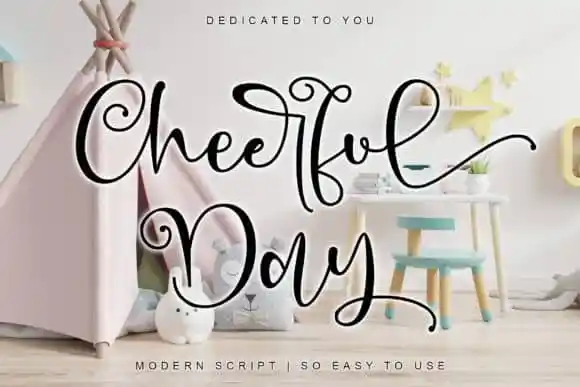
Cheerful Day Calligraphy Font – Download Grátis
Introduzimos a Cheerful Day Calligraphy Font – uma fonte delicada e romântica, escrita à mão com seu fluxo poético. Inspirada no desenho natural da escrita, esta fonte foi projetada e compartilhada por Thomas Aradea. A Cheerful Day possui um estilo elegante e fluido. Ela é perfeita para design de cartas de casamento, cartões de agradecimento, citações e cartões de saudação. Também se destaca em logotipos, cards empresariais e em qualquer outra aplicação gráfica que exige um toque autêntico da escrita à mão. A Cheerful Day apresenta uma variável linha base, linhas suaves, símbolos encantadores e alternativas impressionantes. Perfeita para decorar design com um toque delicado e romântico. Não perca essa fonte elegante que se adequa a todos os estilos de projeto que buscam uma atmosfera natural e poética em seus projetos gráficos.